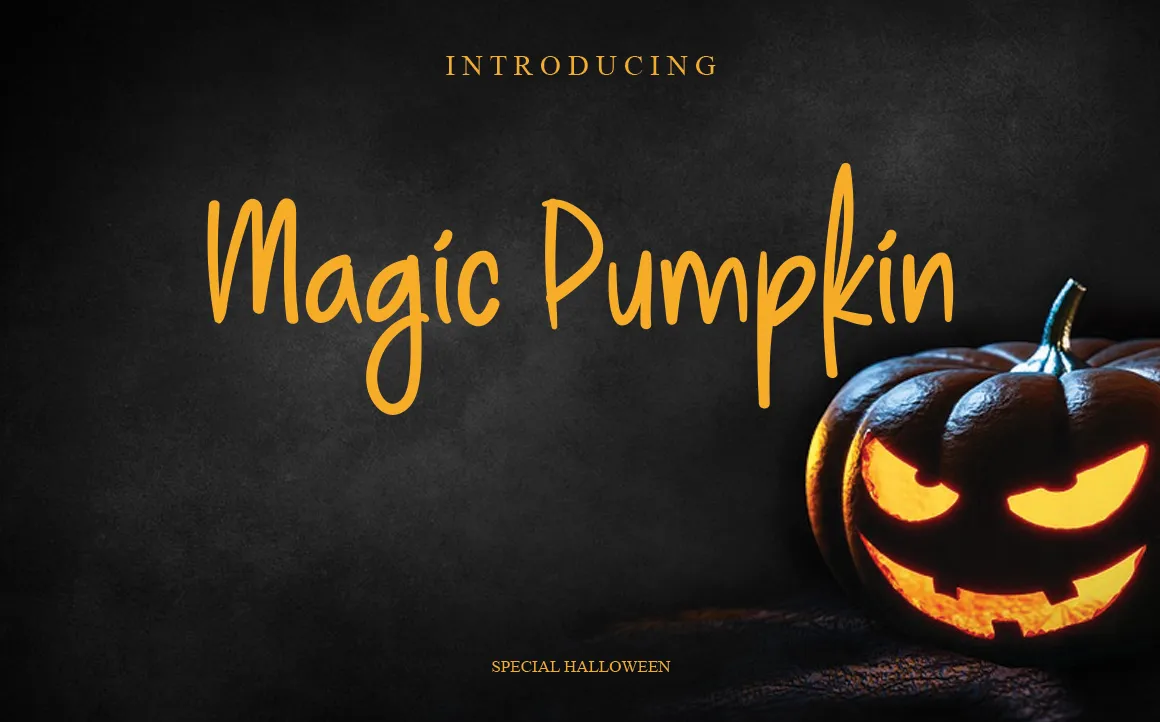
Magic Pumpkin Font – Download Grátis
Esta é uma fonte handwritten única, divertida e amigável. Ela combina tanto para criações digitais como para projetos DIY que exigem estilo elegante. Se você está buscando a perfeita fonte para suas ideias criativas no Instagram ou mesmo para um projeto de calligrafia artesanal, esta font trará qualquer idéia à vida como uma verdadeira obra de arte. Composta pela designer LevinCreative, o Magic Pumpkin Font é o ideal para quem deseja dar vida a projetos digitais com um toque único e elegante.